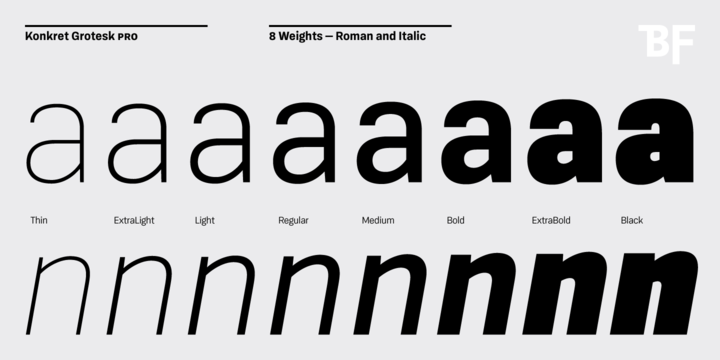
Типографика, с одной стороны, представляет собой одну из отраслей графического дизайна, с другой – свод строгих правил, определяющих использование шрифтов.
Что же такое шрифт? Это графический рисунок начертания букв и знаков.
Семейство всех начертаний шрифта принято называть гарнитурой.
Начертания могут отличаться по насыщенности, наклону и т.д.
Различное начертание шрифтов образует семейство шрифтов — гарнитуру.
Для того, чтобы выбрать гарнитуру, необходимо определиться со стилистикой своего проекта. Тут решающую роль играет контекст вашего сайта. Будет ли выбранная гарнитура уместна?
Учитывайте настроение, которое передаёт шрифт.
Главным критерием классификации видов гарнитур являются засечки на буквах.
В этой статье мы детально разберём гарнитуры, которые встречаются на сайтах.
Обратите внимание на засечки в написании букв.
Антиква — вид шрифта с засечками, поэтому обычно в названии есть слово serif («засечка»).
Популярная антиква: Times New Roman.
Строгое классическое написание букв используется в бумажных книгах, журналах. Засечки в таком случае повышают узнаваемость букв и облегчают чтение.
Гротеск — вид шрифта без засечек, поэтому в названии используется слово sans(«без»).
Популярные представители гротеска: Arial, Helvetica, Verdana.
Неформальное написание шрифта даёт представление о чем-то современном и легком.
Брусковый — вид шрифта, являющийся симбиозом первых двух — антиквы и гротеска. В названии используется slab serif.
Выглядит современнее антиквы.
В большинстве случаев именно такой шрифт применяют в детской литературе — засечки повышают узнаваемость букв ребёнком.
Существуют также художественные шрифты: художественный и акцидентный, которые применяются исключительно для визуального восприятия.
Они не годятся для набора основного текста и предназначены для заголовков и других небольших отрывков текста с целью привлечения и акцентирования внимания.
К акцидентным можно отнести и готические гарнитуры, по рисунку имитирующие средневековые рукописные почерки.
С гарнитурами на разобрались. Далее по плану другие, не менее важные термины типографики: кегль, интерлиньяж, кернинг, трекинг, висячая строка, графема, глиф, выключка.
Не разбегайтесь слишком быстро, на самом деле тут многие вещи интуитивно понятны.
Кегль — размерность символа по высоте. Обычно задается в пикселях(px).
Интерлиньяж — расстояние между двумя строками, дословно переводится «написанное между строк». Задается интерлиньяж всегда относительно величины кегля — в 1,3 — 1,4 раза больше данного значения.
Кернинг — расстояние между двумя отдельными буквами в зависимости от их формы.
В таком случае можно регулировать это расстояние, чтобы написание было равномерным.Если кернинг — расстояние между двумя буквами, то трекинг — расстояние между всеми буквами в слове.
Из понимания этих понятий переходим к висячей строке. Висячая строка — это одинокое слово, которое оторвали от остального текста и отправили одного на новую строку. Это распространённая ошибка, режущая глаз дизайнеру. Используйте трекинг чтобы избежать её.
Графема и глиф. Простыми словами графема — это буква, глиф — стиль её написания.
Выключка — выравнивание текста. По правому краю, по левому краю, по центру, по ширине.
Шрифты типа новых гротесков 50-е гг. XX в. на примере гарнитуры Универс (Univers)
2.1. Эстетические и технические особенности шрифтов типа Гротеск
Шрифты без засечек. Называются также рубленые шрифты, Grotesk (в Германии), Grotesque (в Англии и Франции), Gothic (в Америке).
Впервые наборные шрифты без засечек появились в начале XIX века в Англии, хотя подобная форма знаков применялась еще в надписях античной Греции.
Вначале применялись исключительно как акцидентные, но в ХХ веке стали использоваться для набора текста. Характеризуются, как правило, малой контрастностью или полным отсутствием визуального контраста между основными и соединительными штрихами.
В соответствии с формой овалов, наличием или отсутствием контраста, степенью открытости знаков и степенью разноширинности гротески делятся на старые, новые, геометрические и гуманистические. Иногда к гуманистическим гротескам относят также так называемую ленточную антикву – умеренно контрастный шрифт без засечек, конструкция которого повторяет один из видов антиквы.
Старые гротески (Grotesque)
Первый гротеск появился в 1816 году в Англии. Самые первые из появившихся гротексков. К ним относятся Franklin Gothic и Akzidenze Grotesk. По форме букв они очень близки к гарнитурам антиквы, за вычетом засечек.
Это шрифты с небольшим контрастом, одноширинные, полузакрытые и открытые. Знаки имеют простую и даже грубую геометрическую форму. Шрифты в целом оставляют впечатление сурового грубого реализма.
Новые гротески (Neogrotesques)